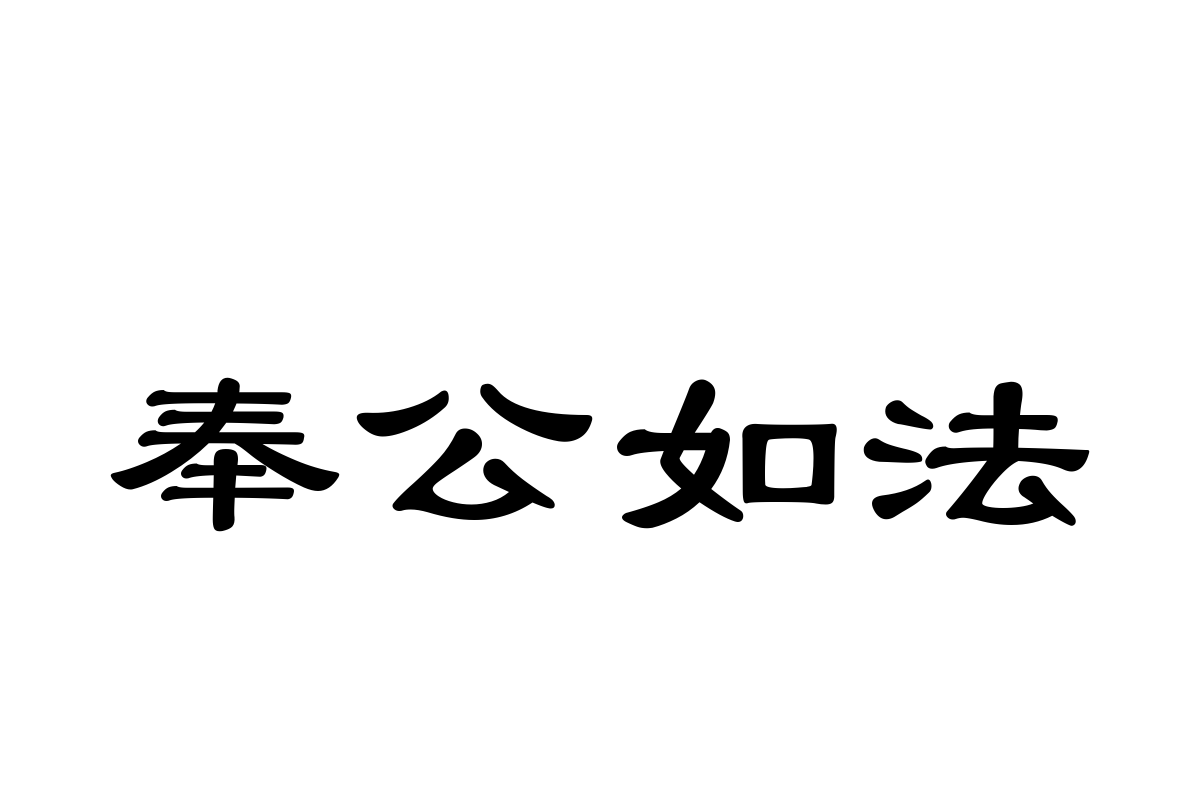
三极隶书简体是一种书法字体,由三个部分组成:隶书、楷书和篆书。这种字体结合了这三种字体的特点,形成了一种独特的风格。
1. 隶书部分:隶书是中国古代的一种书写字体,起源于秦朝,盛行于汉朝。隶书的特点是笔画粗细有度,结构紧凑,线条流畅。在三极隶书中,隶书部分的笔画更加粗犷,线条更加有力,给人一种豪放的感觉。
2. 楷书部分:楷书是中国书法中的一种规范字体,起源于汉末,盛行于魏晋南北朝。楷书的特点是笔画清晰,结构严谨,线条规整。在三极隶书中,楷书部分的笔画更加清晰,线条更加规整,给人一种整洁的感觉。
3. 篆书部分:篆书是中国书法中的一种古老字体,起源于商朝,盛行于周朝。篆书的特点是笔画圆润,线条流畅,结构紧密。在三极隶书中,篆书部分的笔画更加圆润,线条更加流畅,给人一种古朴的感觉。
总的来说,三极隶书简体是一种融合了隶书、楷书和篆书特点的书法字体,既有隶书的豪放,又有楷书的清晰,还有篆书的古朴。这种字体既保留了传统书法的韵味,又展现了现代审美的趋势。